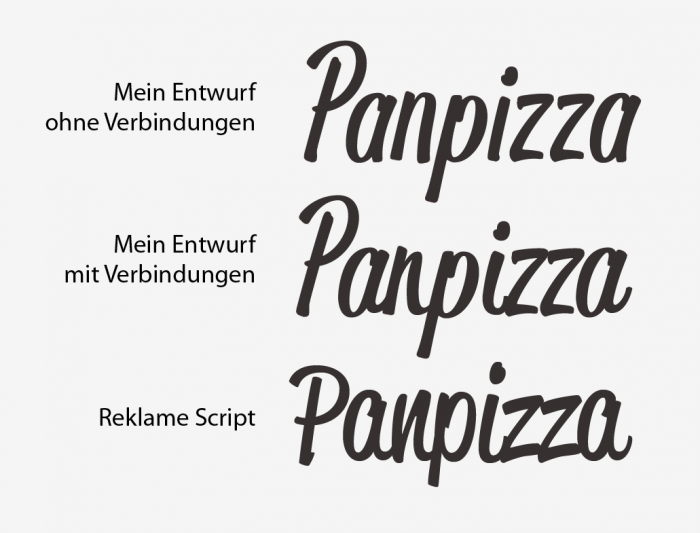
Zu große Ähnlichkeit zu bestehender Schrift
ich bin leicht am verzweifeln...
Im Juli habe ich meinen allerersten Freefont veröffentlicht und experimentiere seitdem in Illustrator mit einer Handschrift (genauer: eine coole Retro-Pinselschrift soll es werden). Über dem Projekt schwebte von Beginn an das große Vorbild "Reklame Script" von Hannes von Döhren. Mein Entwurf hat sich seit Juli diverse Male verändert und ist dabei Reklame Script leider immer ähnlicher geworden. Mit der letzten Fassung war ich heute nun plötzlich wieder mal unzufrieden und habe die Glyphen miteinander verbunden – mit dem Ergebnis, dass mein Entwurf jetzt fast eine 1:1-Kopie ist. Es ist, als hätte ich die letzten 5 Monate in eine Sackgasse hinein gearbeitet...
Hat jemand einen Tipp, wie ich meinen Entwurf verbessern kann, ohne einer bestehenden Schrift wie Reklame Script zu nahe zu kommen?
Ich glaube du wirst kein zufriedenstellendes Ergebnis erhalten, wenn du deiner Schrift jetzt eine Detailanpassung aufzwängst.
Deine Schrift ist schräger gestellt, vielleicht kannst du an diesem Punkt weiter arbeiten und z.B. das n anpassen (wohl leider in Richtung der Reklame),
dafür hat dein Minuskel-p mehr Schwung und dein z gefällt mir auch besser, weil es die Grundlinie nicht anknabbert.
Dein i-Punkt könntest du durch einen Strich ersetzen, das kann die Wirkung auch schnell beinflussen.
Vielleicht könntest du deine Endstriche auch nicht mehr überlappen lassen, das könnte auch noch eine Option sein.
Du könntest auch die Weite verändern und zum Beispiel noch etwas breiter werden (das würde sie bei mehr Schräglage ohnehin vertagen).
Und warum lässt Du den Entwurf ohne Verbindungen nicht einfach drin und legst ihn als Opentype-Alternative an? Dann kann der Anwender selber entscheiden, was gerade besser passt. Außerdem hätte die Schrift gegenüber ihrem Vorbild dann einen deutlichen Mehrwert.
Des Weiteren könntest Du an den Ellipsen feilen – einem klareren Formenprinzip folgen. Zum Beispiel wie beim P auch beim a, d, p, q, … noch oben offener werden.
Ich würde mir an Deiner Stelle auch noch eine andere Schreibschrift* als Inspirationsquelle hinzu zu ziehen, um mich nicht zu sehr an der Reklame fest zu beißen. So toll ist sie ja nun auch wieder nicht.  ;-)
Ich bin versucht zu sagen die Variante ohne Verbindungen ist die stärkere der beiden, und die, die weiter weg ist vom Vorbild ... das halte ich durchaus für verfolgenswert.
Die Variante mit Verbindungen braucht natürlich noch viel Feintuning in den Formen, Verbindungen, Abständen und Wiederholungsvermeidung, und würde bestimmt am Ende besser aussehen als jetzt, aber da mühst du dich eben in eine Richtung der Ähnlichkeit, nicht weg davon.
Eventuell könntest du auch bei der ersten Variante bleiben, und ihr stilistische Varianten für Doppelbuchstaben, und Sonderformen für Wortanfänge und Enden mitgeben.  In deinem Beispiel sähen dann die beiden "a" und "z" schon nicht mehr exakt gleich aus, was eine Handschriftlichkeit mit sich bringt, die auch ohne Verbindungen auskommt.
Ich bin versucht zu sagen die Variante ohne Verbindungen ist die stärkere der beiden, und die, die weiter weg ist vom Vorbild ... das halte ich durchaus für verfolgenswert.
Die Variante mit Verbindungen braucht natürlich noch viel Feintuning in den Formen, Verbindungen, Abständen und Wiederholungsvermeidung, und würde bestimmt am Ende besser aussehen als jetzt, aber da mühst du dich eben in eine Richtung der Ähnlichkeit, nicht weg davon.
Sehe ich auch so.
Eventuell könntest du auch bei der ersten Variante bleiben, und ihr stilistische Varianten für Doppelbuchstaben, und Sonderformen für Wortanfänge und Enden mitgeben.  In deinem Beispiel sähen dann die beiden "a" und "z" schon nicht mehr exakt gleich aus, was eine Handschriftlichkeit mit sich bringt, die auch ohne Verbindungen auskommt.
Beispiele dafür: FF Duper, Romp, St Florence
Auch weitere Pseudo-Handschriftlichkeit lässt sich einbauen, z.B. sich aus dem Schreibfluss einfach ergebende Verbindungen wie "ft" oder "tz", Sonderformen für Zwie- und Umlaute, für ch, sch und ck, oder auch Sonderformen vor oder nach bestimmten anderen Buchstaben, um gewisse Kollisionen elegant zu umgehen (z.B. f vor allen Zeichen mit Oberlänge). Das bringt einfach etwas mehr Detailvariation rein und macht die Schrift handschriftlich, auch wenn die Buchstaben sich nicht verbinden.
Bedenke nur, erst mal das Grundalphabet soweit zu bringen dass es dir passt – in Form und Metrik, und erst dann die Varianten davon abzuwandeln und diese dann eins nach dem anderen sauber ins Grundalphabet zu integrieren, sonst halst du dir schnell mehr Arbeit auf als nötig.
Danke für die vielen, konstruktiven Antworten! Leider bin ich (noch) nur mit Type Tool 3 ausgestattet, womit Opentype-Funktionalitäten und ausgefallene Ligaturen meines Wissens nach nicht möglich sind... außerdem bin ich noch nicht sehr erfahren – das ist erst meine 2te Schrift und mit 2 Schnitten für mich schon ein sehr großes Projekt. Ich werds wohl wie im letzten Post von Sebastian machen und erstmal mein Grundalphabet komplettieren... dann sieht man weiter.
Ich selbst habe übrigens oft solche Schriftnutzer, die mit OpenType-Funktionen hoffnungslos überfordert sind. Möchte ich hier z.B. Schwung-Abschlussformen, oder spezielle Formen für problematische Paarungen anbieten, greife ich zu einem gänzlich anderen Trick: Die Sonderformen kommen dann einfach in einen „kursiven“ oder „fetten“ Font mit gleichem Familiennamen. Damit ist es dann auch mit nicht OpenType-fähigen Programmen möglich, Anlternastivformen zu aktivieren.